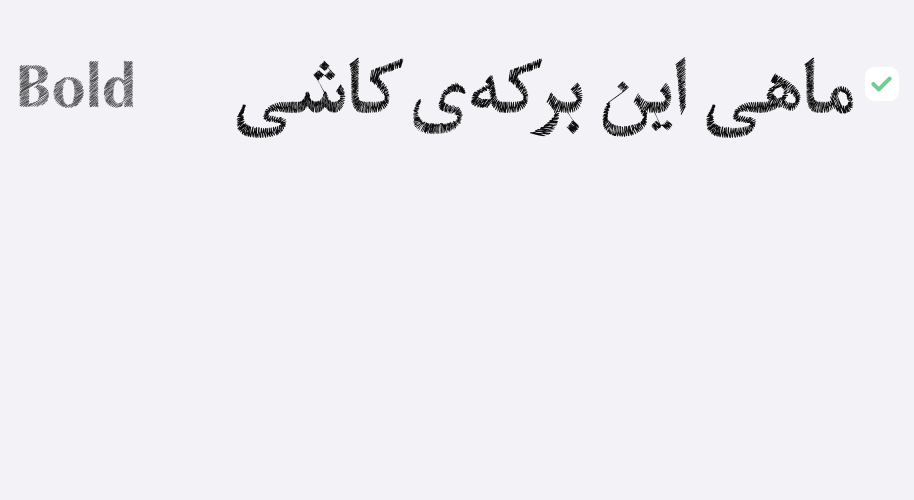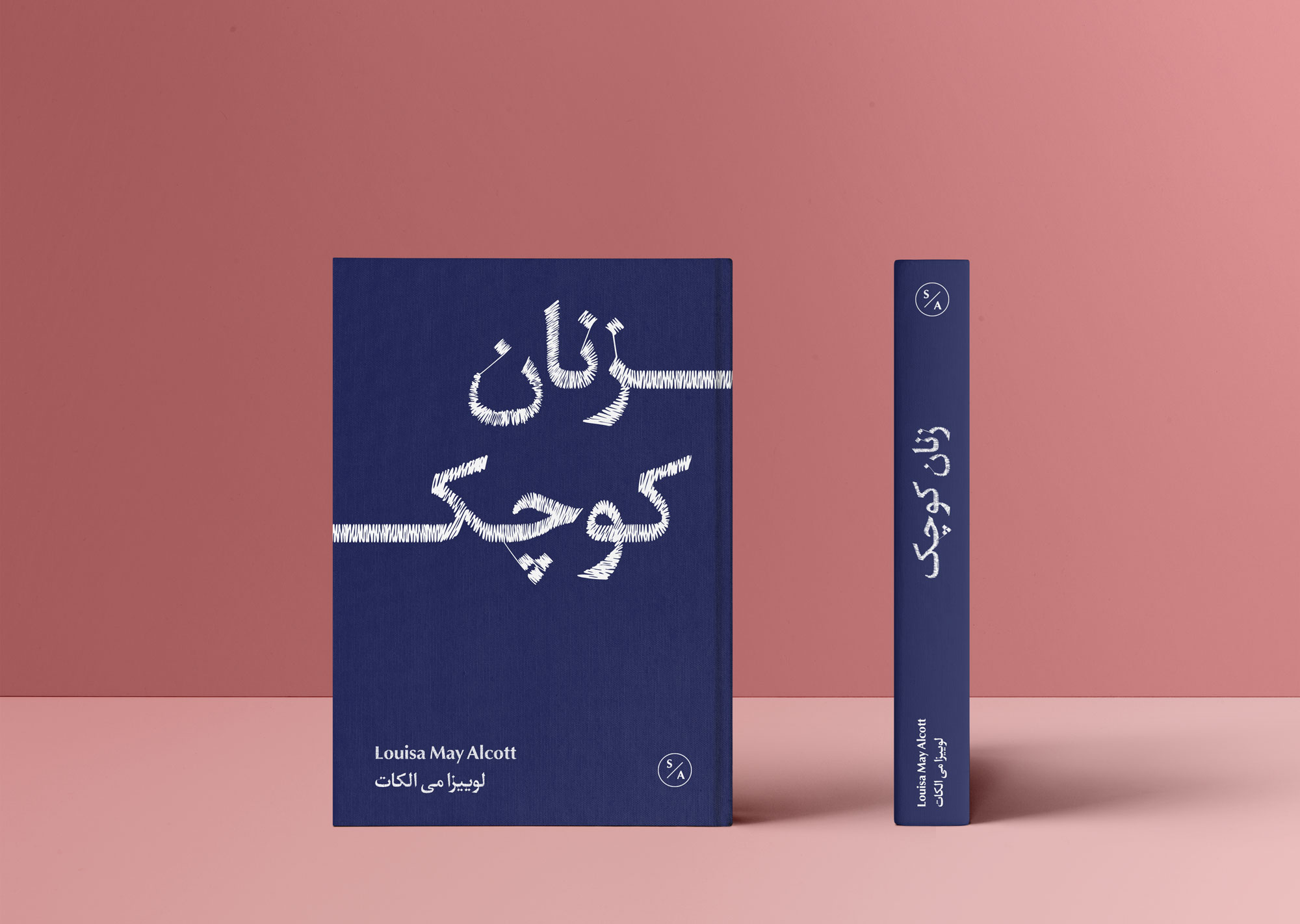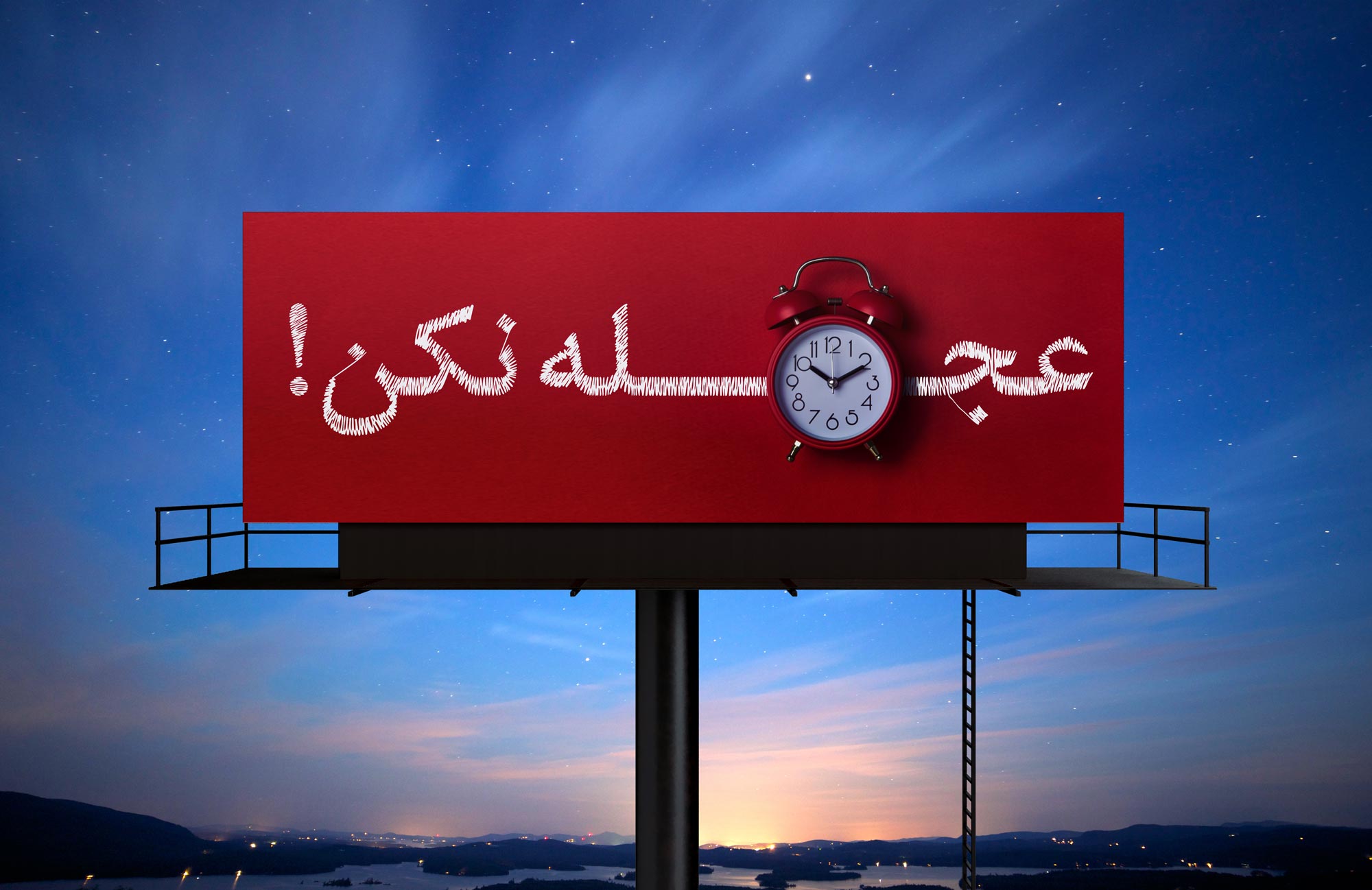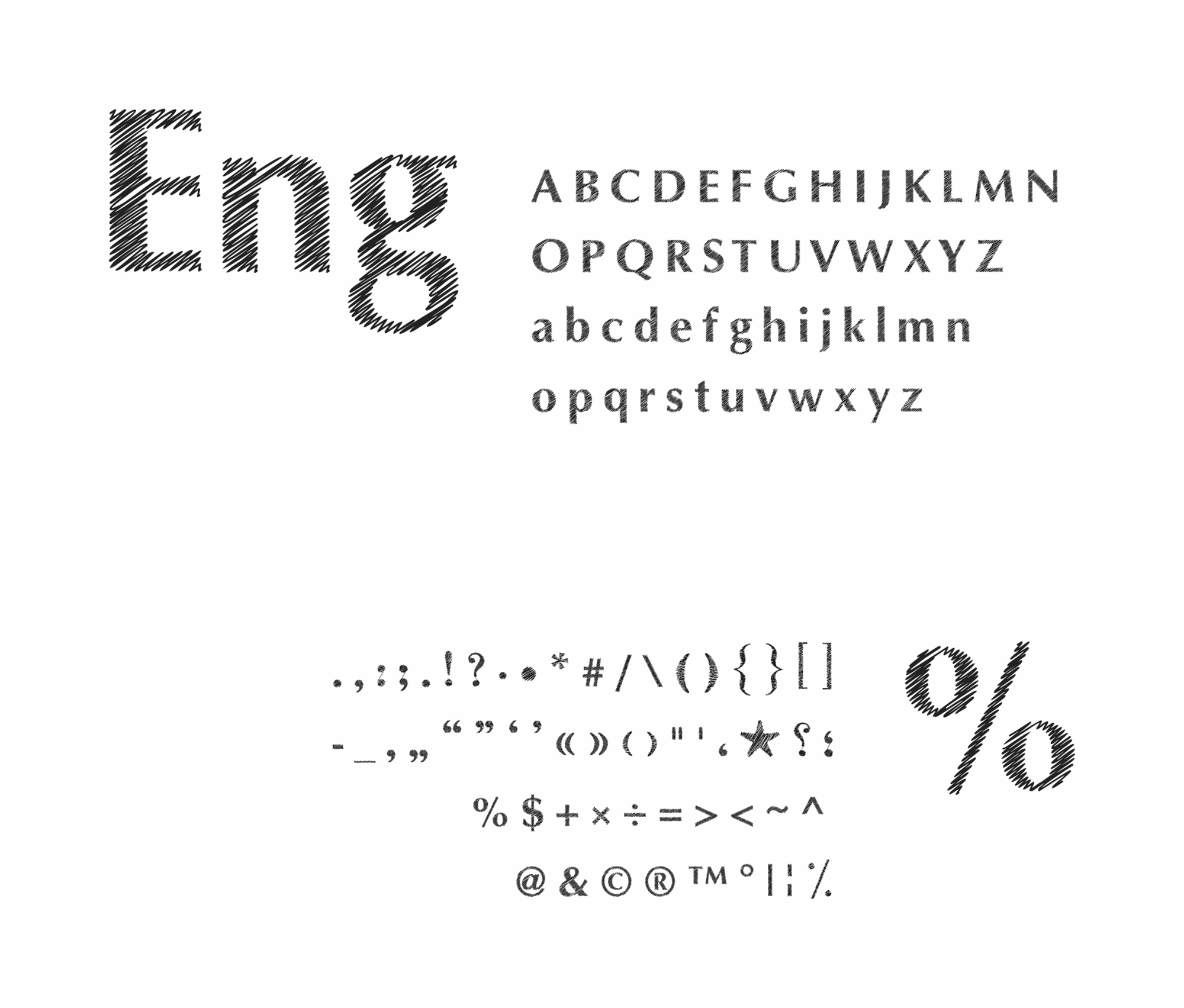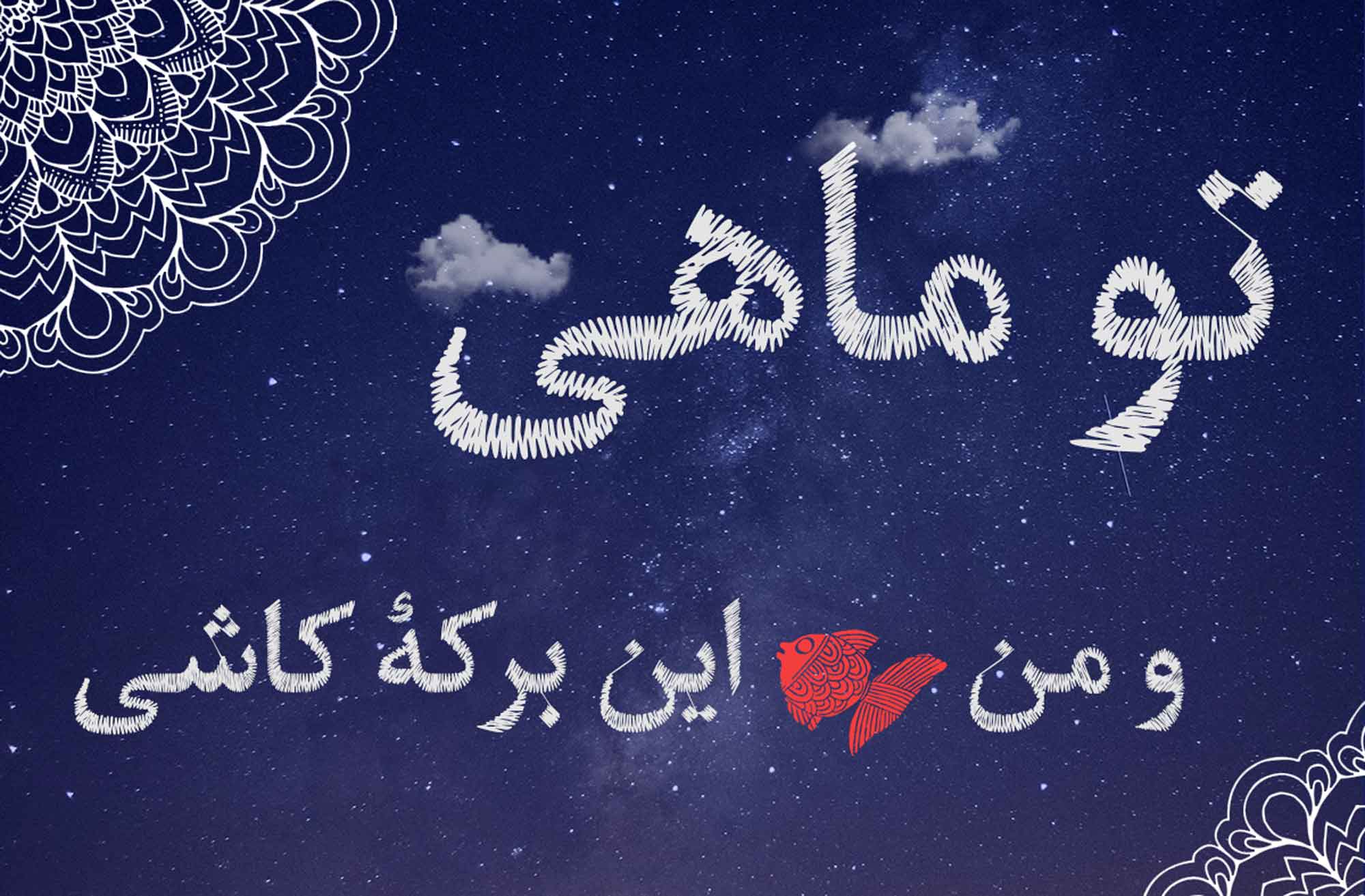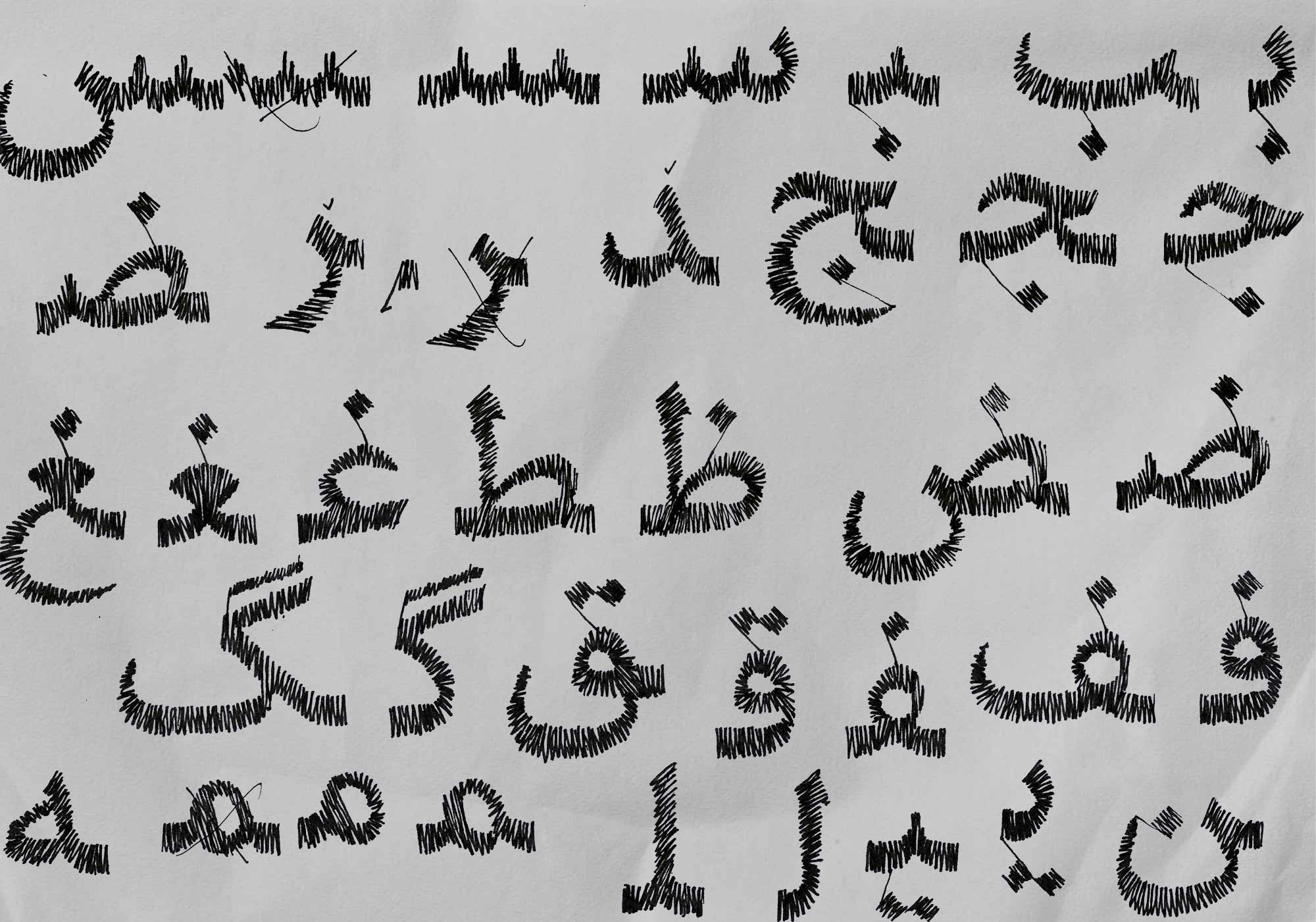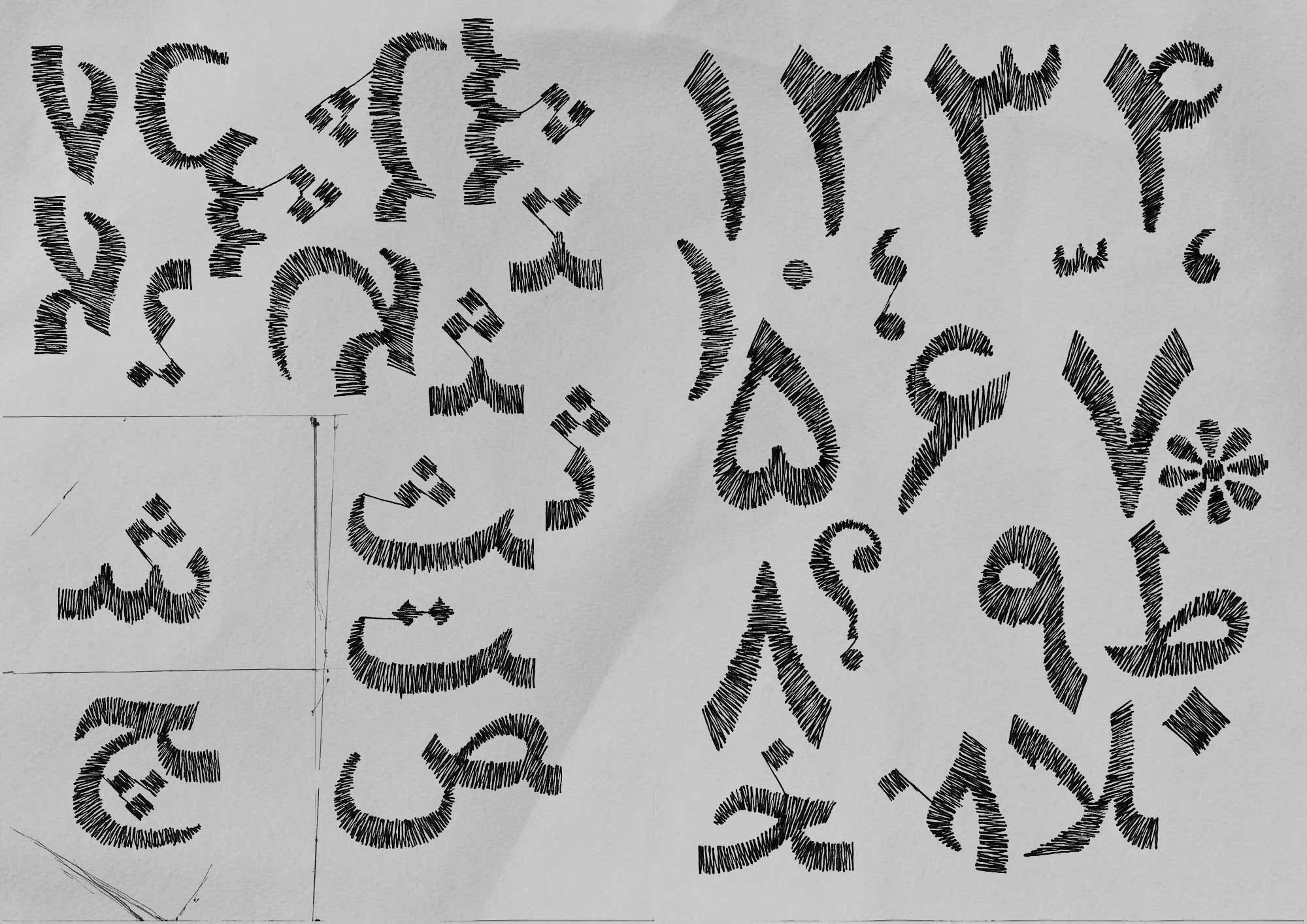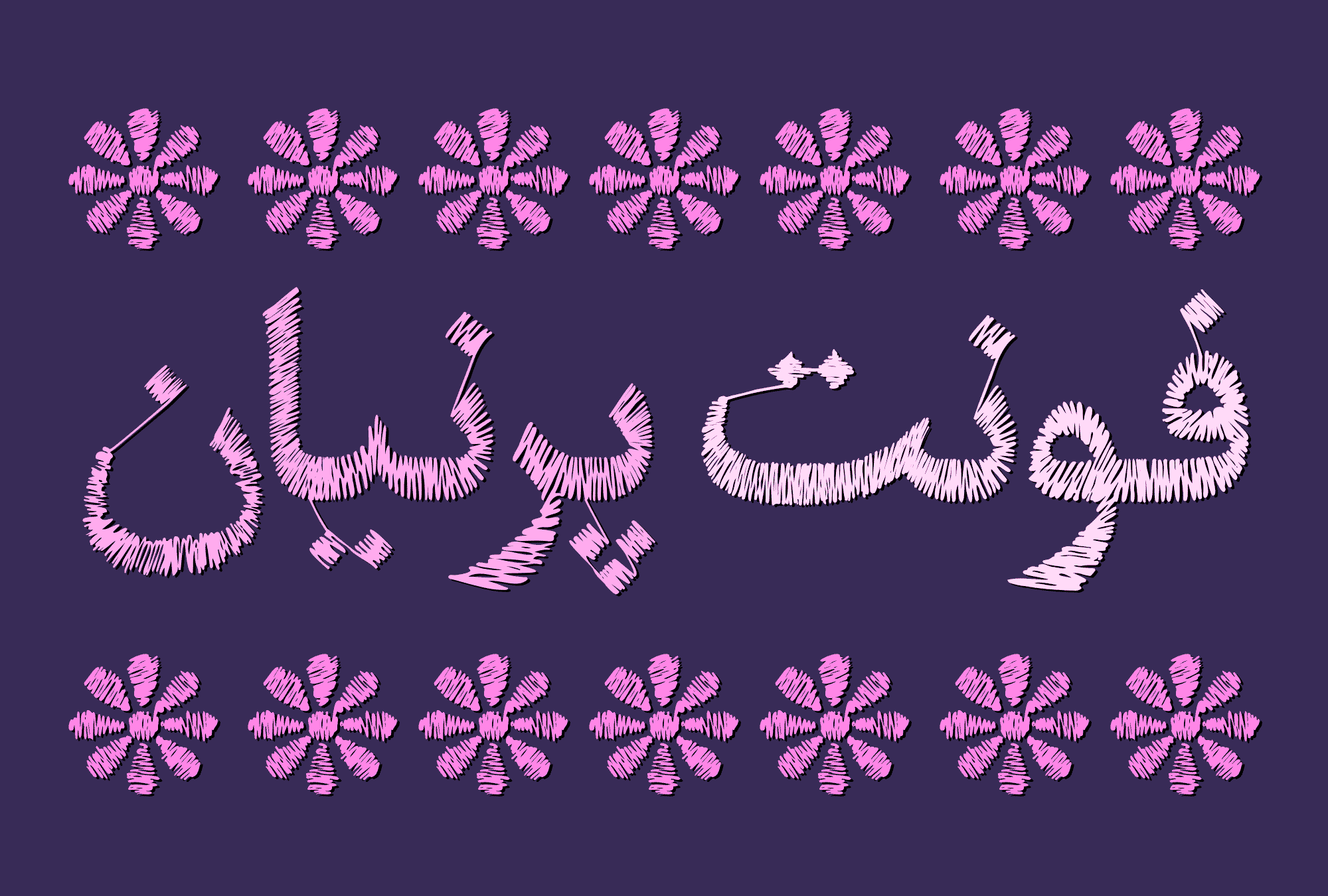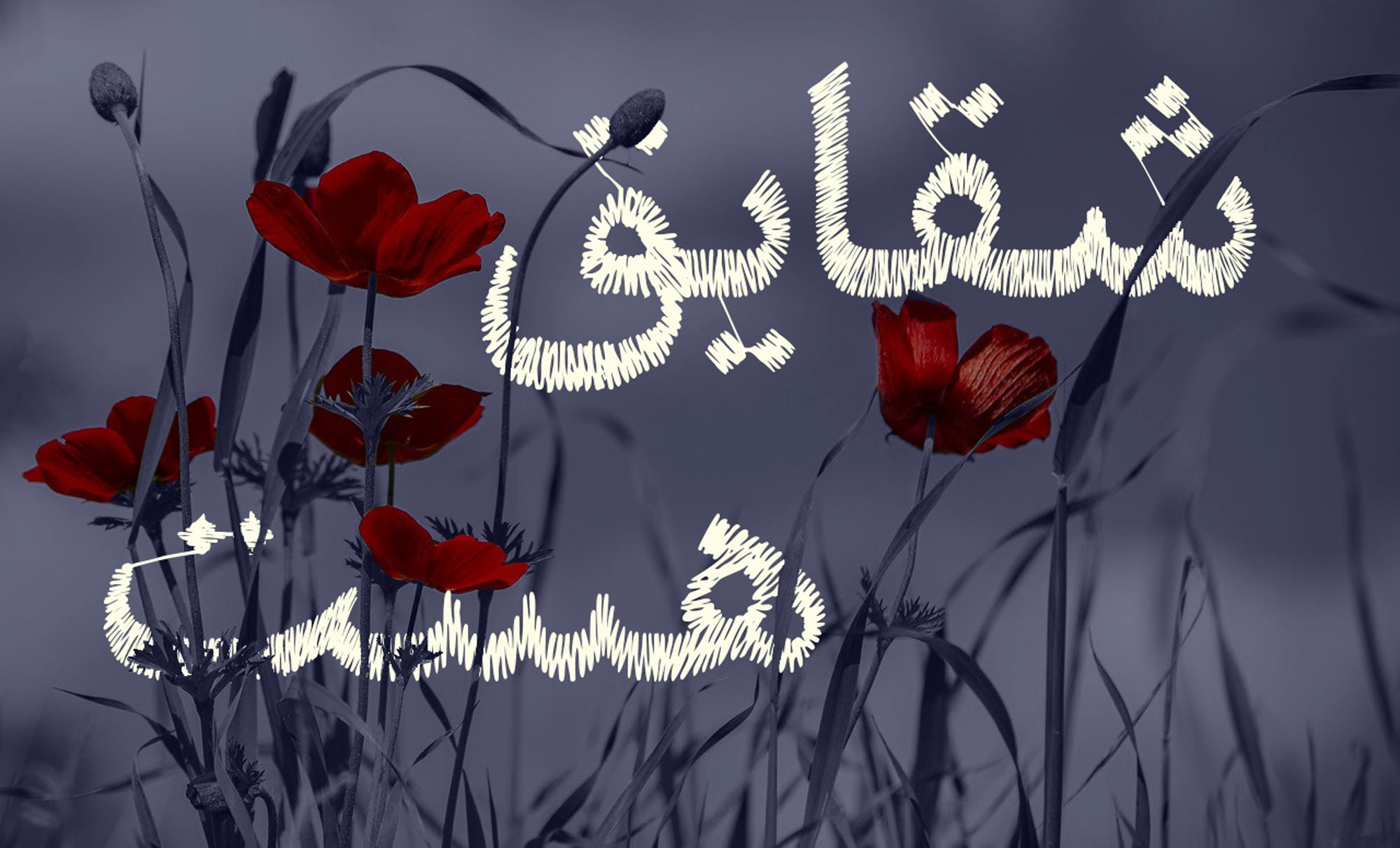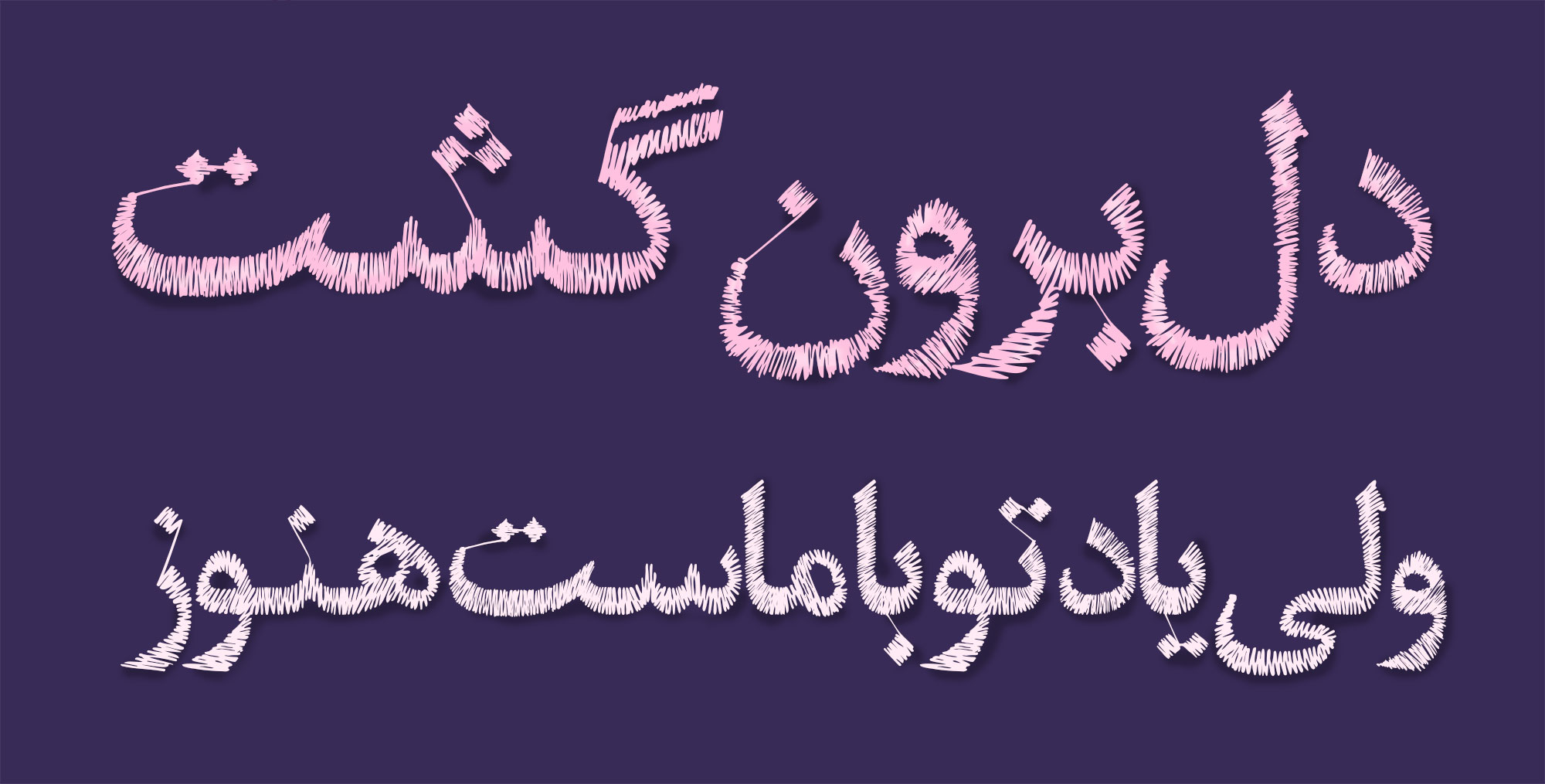
فونت پرنیان از زبانهای فارسی، عربی و انگلیسی پشتیبانی میکند.
فونت پرنیان بصورت دستی طراحی شده اسن. حرکت نخ در گلدوزی توسط قلم شبیه سازی شده سپس حروف عکاسی و به فایل برداری تبدیل شده است.
پرنیان کاشفی فارغ التحصیل کارشناسی گرافیک است و فونت پرنیان را در قالب پروژه دانشجویی در کارگاه طراحی حروف مسلم ابراهیمی طراحی کرده است.